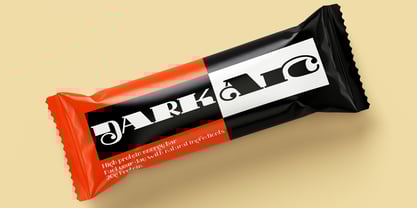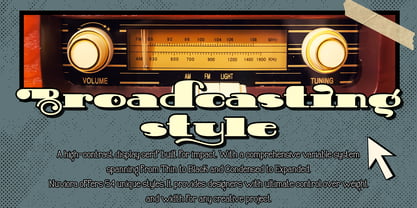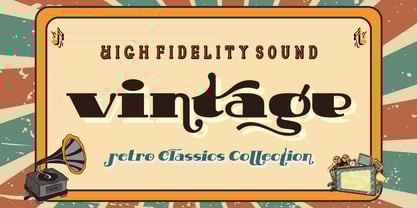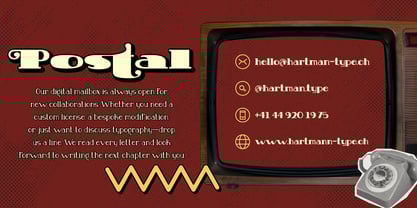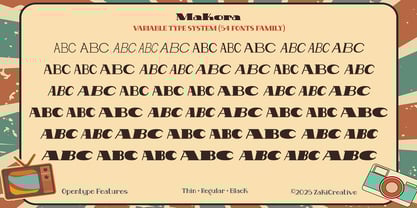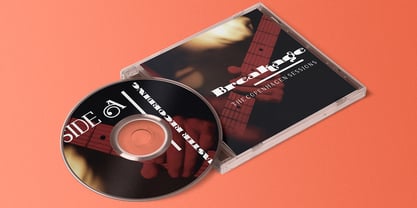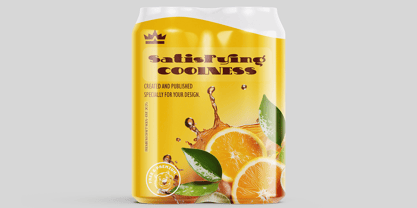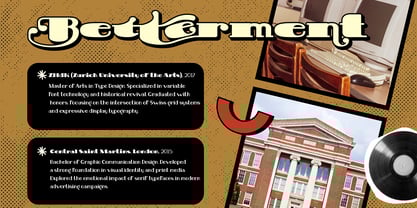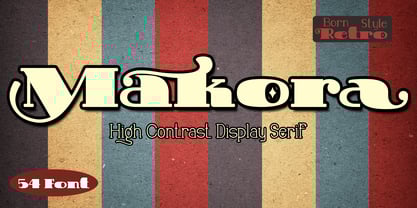
Makora Variable
La familia tipográfica Makora Variable fue diseñada por Teuku Muhammad Zaki y publicada por Zaki Creative. Makora Variable contiene 55 estilos y opciones de paquete familiar.
Makora — A High-Contrast Retro Variable System Rediscover the Soul of 70s Typography. Makora is a comprehensive display type system designed to bridge the gap between the groovy, voluptuous aesthetics of the vintage era and modern digital precision. Crafted with soft, flowing curves and razor-sharp serifs, Makora delivers a high-contrast visual punch that demands attention. Power in Versatility: Why settle for one look when you can have them all? Makora comes equipped with a massive 54-style family, ranging from the elegant Thin Condensed to the dominating Black Expanded. Whether you need a whisper or a shout, Makora adapts perfectly to your layout. Key Features: 54 Styles: An extensive range of Weights (Thin to Black) and Widths (Condensed to Expanded) to suit any space. Variable System: Includes a variable font file allowing for infinite control over weight, width, and slant axes for precise customization. Expressive Typography: Loaded with standard ligatures, discretionary ligatures, and stylistic alternates to give your headlines a custom, hand-lettered feel without the extra effort. Global Language Support: Extensive character set supporting multiple languages for international creative projects. Perfect For: Luxury branding, retro vinyl covers, bold packaging design, editorial headlines, fashion magazines, and poster art that needs a touch of modern nostalgia. Elevate your design game with Makora. Bold. Groovy. Timeless.